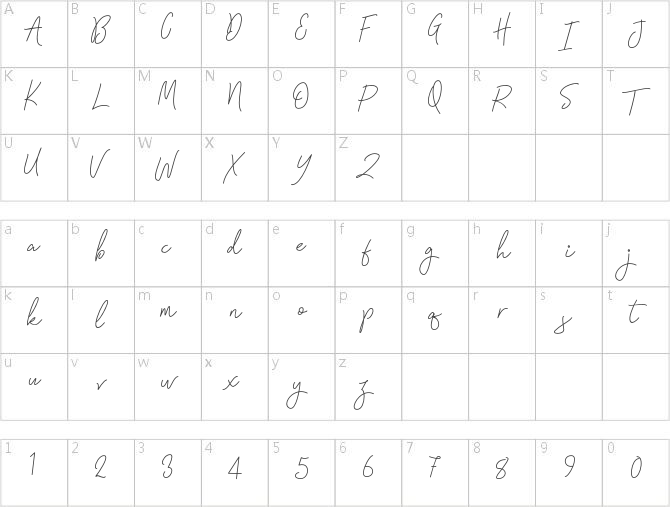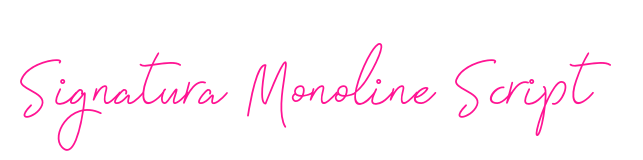
Signatura Monoline Script
Signatura Monoline Script介绍
Signatura Monoline Script字体字库是一款让人赏心悦目、百看不厌的英文字体,适合各类广告和产品包装设计应用,字体大小0.04MB,格式为otf字体,上传用户是dqq520,作者/版权方为未知